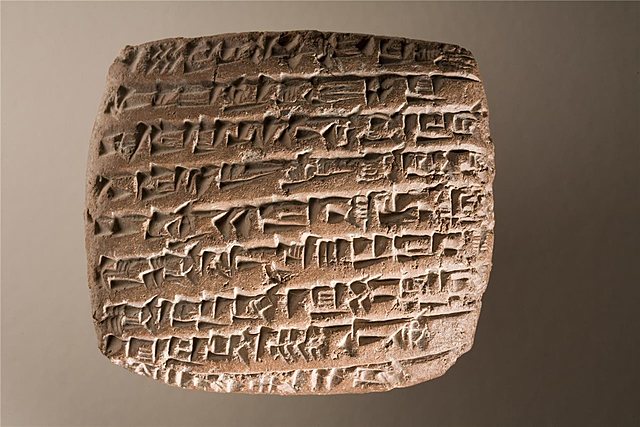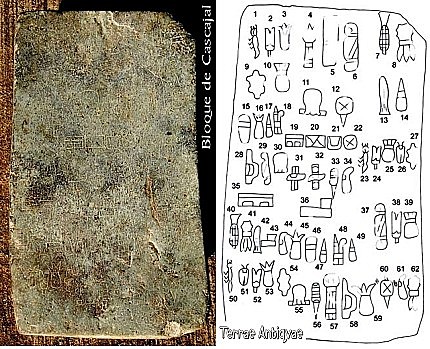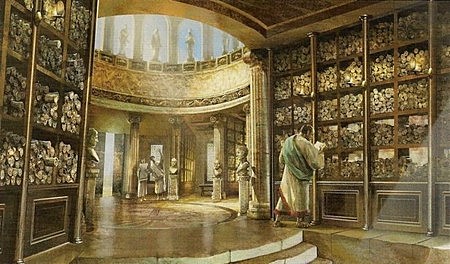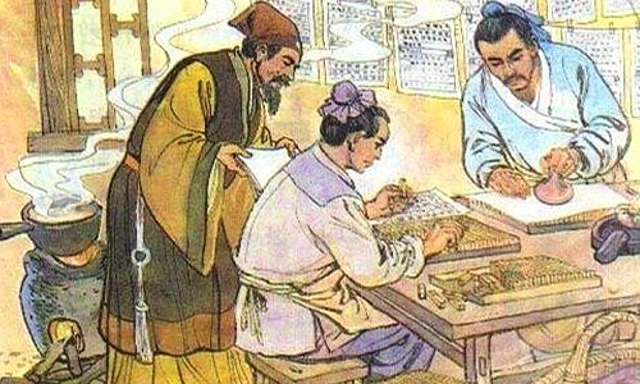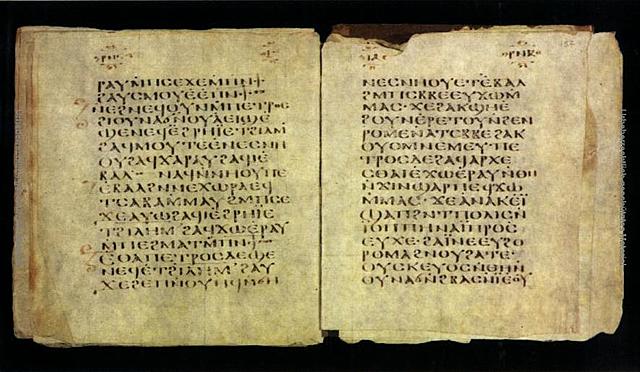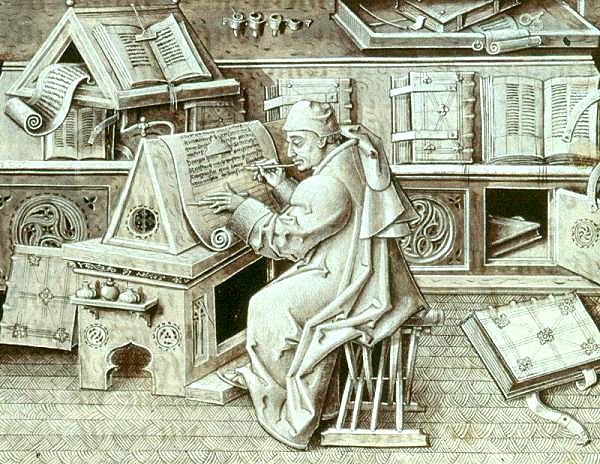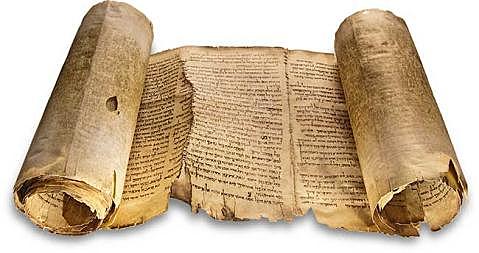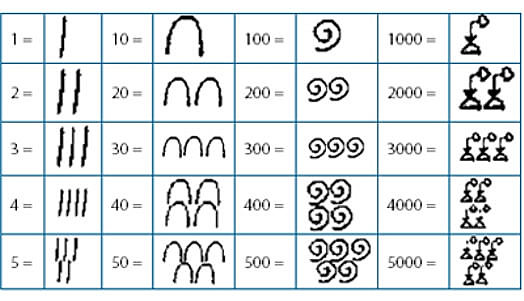
Las tablillas de arcilla fueron utilizadas en Mesopotamia desde el 3000 a.C.
El stilus, un instrumento a manera de triángulo, servía para inscribir en bloques de barro los caracteres de una escritura en forma de cuña (por esta razón se le llama cuneiforme). Estas piezas eran cocidas después para darles solidez y durabilidad. -
parece que los egipcios se adelantaron en casi un milenio, ya que en tiempos de la primera dinastía este pueblo contaba con un sistema decimal funcional que podía seguir el cómputo de hasta millones de unidades. Se le denomina sistema numeral hierático. Existía una serie de símbolos o signos separados para cada número hasta el nueve y para cada potencia de 10. No obstante, no conocieron el número cero.
Como soporte de escritura, desde 2800 a.C., los egipcios usaron el papiro, planta abundante a orillas del Nilo. Seccionaban su corteza en finas láminas y las colocaban en bandas cruzadas; al secarse, la savia servía como pegamento, luego se blan- queaba y pulía la superficie. Los egipcios lo comercializaban en forma de rollo de 20 hojas. El término volumen se refiere al acto de enrollar o envolver un papiro.
Cuando Egipto prohibió la exportación de papiro, en la ciudad asiática de Pérgamo se empezó a utilizar piel curtida, raspada, raída y preparada para la escritura, llamada pergamino; éste dio origen al códex. Los testimonios del uso datan del 2700-2500 a.C. y el pergamino más antiguo que se conserva data del siglo II a.C.
En Mesoamérica la escritura se desarrolló de manera independiente a través de un sistema de signos que combinaba logogramas con elementos silábicos. Se labraban en piedras o estuco, o bien, eran pintados sobre tiras de piel animal, cortezas o fibras vegetales, para formar los llamados códices.
La numeración arábiga, denomina al sistema numérico que empleamos en la actualidad. Nació en la India hacia el siglo V a.C. Algo que debes tener claro para comprender la historia de los números. Existe representación de los números 1, 4 y 6 en las inscripciones budistas de Asoka del siglo III a.C. En otras inscripciones de un siglo más tarde se ven los números 2, 4, 6, 7 y 9 grabados en los monumentos de Nana Ghat. En documentos del siglo II d.C. aparecen ya todos menos el 8.
Con el propósito de preservar el legado de la civilización griega, Alejandro Magno fundó en el siglo III a.C. la Biblioteca de Alejandría, la más grande de su época, pues llegó a albergar más de 500 mil manuscritos, adquiridos en Grecia, el Medio Oriente, la India y África. Esta gran colección fue consumida casi en su totalidad por un incendio.
La invención del papel, a principios del siglo II a.C., se atribuye a Ts’ai Lun. Desde un siglo atrás se elaboraban hojas de seda y lino para envolver objetos, pero este funcionario promovió el uso de fibras vegetales más compactas y ligeras que permitían la escritura con tinta.
Desde el siglo IV el pergamino era el material básico para elaborar los códex medievales. Para escribir se usó primero el cálamo de caña y después las plumas de diversas aves. La tinta solía ser negra para los textos y roja para los títulos e iniciales. Para ahorrar espacio se inventó la letra minúscula.
El scriptorium (término que significa “un lugar para escribir”) era la habitación monástica anexa a la biblioteca, destinada a la copia de manuscritos. A comienzos del siglo XIII, aparecieron escribas profesionales que incluso trabajaron en su domicilio.
Los números actuales aparecieron en la India, donde se inventó hacia el siglo V la aritmética de posición decimal y el uso del 0. El primer ejemplo del uso de la numeración decimal data del 595, en que se incluye el uso funcional del 0: un punto.
Fue allí donde se comenzó a contar del 1 al 10, como hacemos hoy. Existe referencia concreta a la numeración indostánica en una nota escrita por el obispo Severus Sebokht hacia el 650, que habla de “los nuevos signos”. -
En tiempos de las Cruzadas apareció una narrativa de ficción que recreaba las hazañas de personajes legendarios representativos de los ideales caballerescos y cortesanos. Chrétien de Troyes (1135-1190) es considerado el padre de la novela occidental, género que gozó de gran popularidad entre gente letrada hasta el siglo XVI.
Aunque artesanos chinos en el siglo XI y coreanos en el XIII crearon sistemas de reproducción con tipos móviles, la imprenta moderna fue perfeccionada hacia 1450 por Johannes Gutenberg, quien adaptó una prensa utilizada para exprimir uvas y fabricar vino. Se considera que su mejor trabajo fue la Biblia de 42 líneas.
Aparece la primera impresora para aquella época de gran velocidad la UNIVAC que estaba fabricada por Remington-Rand. Esta impresora que ya tenía incorporada una fuente de alimentación propia también tenía un sistema electrónico para controlar el sistema y autocorregir su funcionamiento. La máquina ya tenía 4 rodillos y funcionaba alimentada con cinta, era capaz de escribir 600 lineas de texto en un minuto.